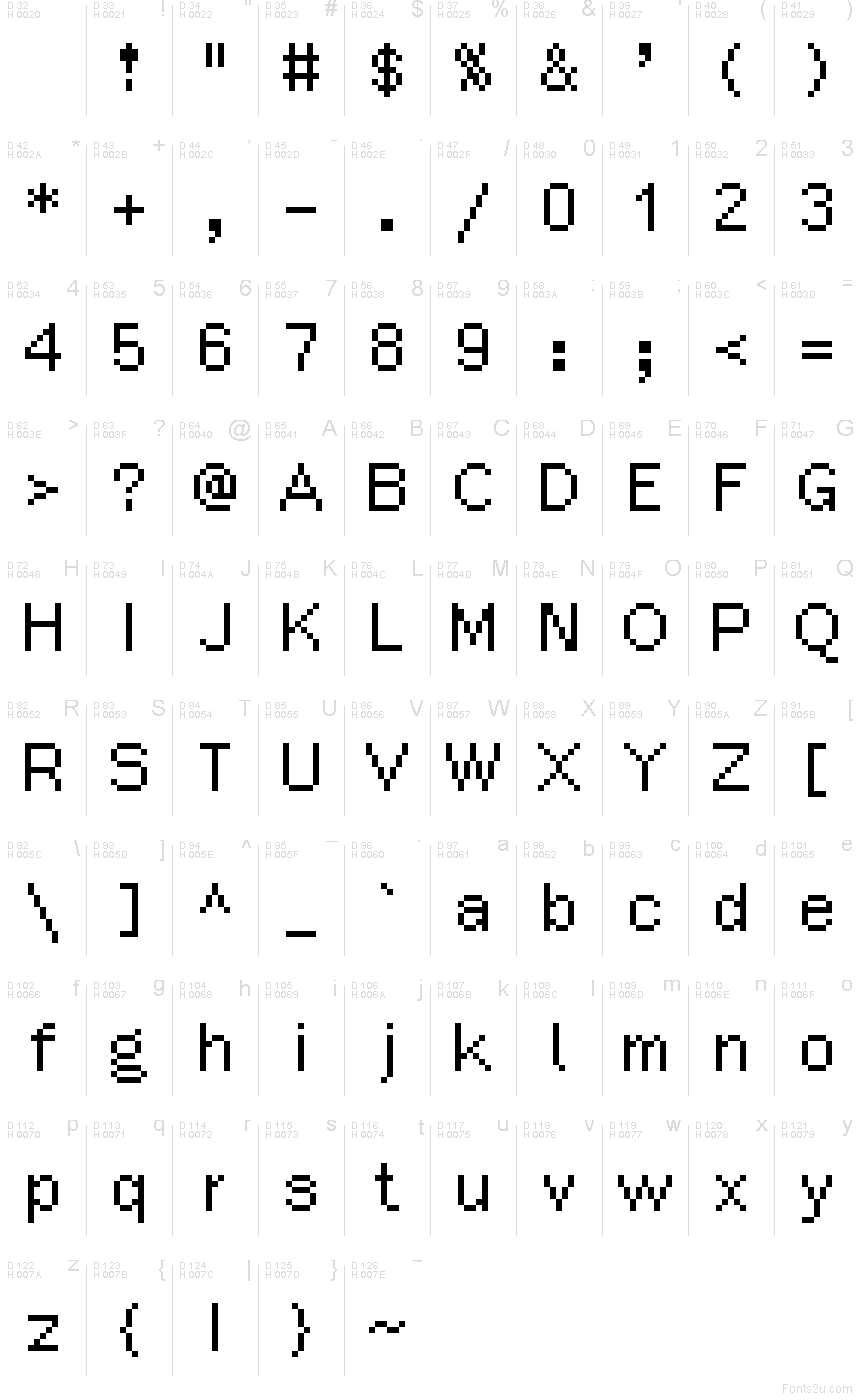
Airmail od MagicBear je bezplatné pixelové titulkové písmo složené z ostrých obdélníkových bloků. Jeho písmena mísí široké blokové tahy s prudkými čtvercovými zářezy, což tvarům dodává robustní, mechanický profil. Drobné odstupňované detaily udržují písmo živé namísto přísně mřížkového.
Designéři pracující na projektech retro her jej shledají velmi vhodným pro titulní obrazovky, grafiku rozhraní a propagační plakáty. Hodí se také na merchandise s technickou tematikou. Čtvercová konstrukce propojuje toto využití s arkádovou grafikou a ranými počítačovými monitory, kde se nápisy často stávaly součástí obrazu na obrazovce.
Gotické / sans-serifové pixelové písmo vytvořené pomocí Fontstruct.
Designer description: <p>A nice and classic Gothic/Sans-serif.</p>